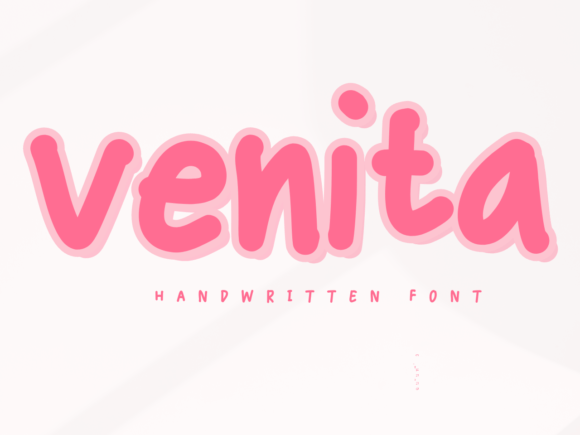
Venita
適切なデザイン要素を見つけるのは難しい場合がありますが、Venitaは作品を即座に引き立てる優れたコレクションを提供します。
精密に作られたVenitaは、クリーンなベクター、滑らかなタイポグラフィ、そして安心のための商用ライセンスを提供します。
POD(オンデマンド印刷)製品、結婚式の招待状、またはソーシャルメディアのグラフィックを作成している場合でも、Venitaは理想的です。